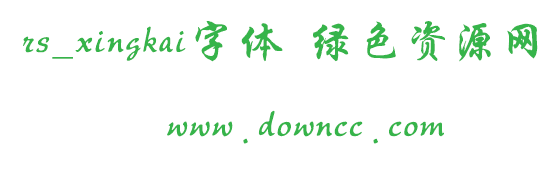
rs xingkai 字體是一款優(yōu)美的四通利方行楷字體,這款字體布局精妙,線條瀟灑流暢,和常見(jiàn)的行書字體有點(diǎn)像,可用作廣告字體,而且在生活的廣告中都是比較常見(jiàn)的,非常的實(shí)用,需要的朋友趕緊來(lái)綠色資源網(wǎng)下載吧!
楷書是以點(diǎn)畫結(jié)構(gòu)為特點(diǎn)的漢字書體,筆法、字形非常的固定。
行楷書的字形是在楷書的點(diǎn)畫基礎(chǔ)上,略加變動(dòng)而適于連筆書寫的一種實(shí)用性很強(qiáng)的書體,是楷書的直接快寫體。